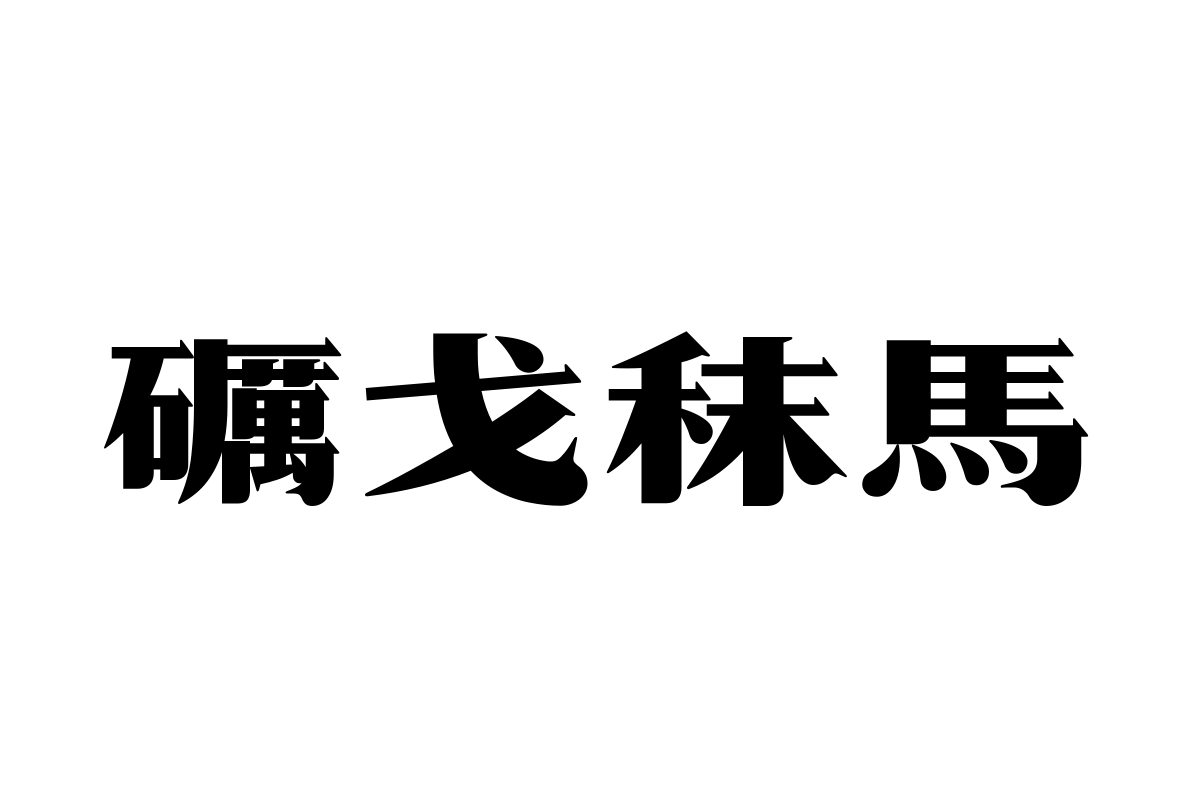
汉仪鹅头宋繁体字体是一款具有独特设计感的中文字体,其特点是笔画圆润、结构紧凑,呈现出一种优雅而流畅的视觉效果。这款字体适用于各种需要展示清晰、整洁的文字排版场景,如书籍、杂志、广告、网页等。
汉仪鹅头宋繁体字体的特点如下:
1. 笔画圆润:汉仪鹅头宋繁体字体的笔画线条流畅自然,没有尖锐的棱角,给人一种柔和的感觉。
2. 结构紧凑:虽然笔画圆润,但整体布局仍然保持了一定的紧凑度,使得文字在视觉上不会显得过于松散。
3. 优雅流畅:汉仪鹅头宋繁体字体的字形优美,线条流畅,给人一种优雅而富有艺术感的视觉效果。
4. 适用范围广:由于其独特的设计特点,汉仪鹅头宋繁体字体适用于各种需要展示清晰、整洁的文字排版场景,如书籍、杂志、广告、网页等。
总之,汉仪鹅头宋繁体字体是一款具有独特魅力和实用性的中文字体,适合用于各种需要展示清晰、整洁的文字排版场景。